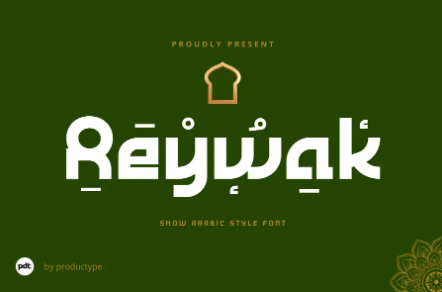
[Creativemarket] Reywak Font (2022)
Reywak - новый впечатляющий шрифт, в котором сочетаются чистый вид шрифтов sans-serif и мощная символика арабских символов. Благодаря своей удобочитаемости он идеально подходит для заголовков и длинных текстов, а уникальная привлекательность арабески прекрасно подходит для плакатов и поздравлений. Reywak: используйте его, чтобы сделать ваш контент лучше других.
Конечно, ваши различные дизайнерские проекты будут идеальными и необычными, если вы будете использовать этот шрифт, потому что этот шрифт оснащен семейством шрифтов, как для заголовков, так и для подзаголовков и текста предложений, начните использовать наши шрифты для ваших необычных проектов.
Reywak - новый впечатляющий шрифт, в котором сочетаются чистый вид шрифтов sans-serif и мощная символика арабских символов. Благодаря своей удобочитаемости он идеально подходит для заголовков и длинных текстов, а уникальная привлекательность арабески прекрасно подходит для плакатов и поздравлений. Reywak: используйте его, чтобы сделать ваш контент лучше других.
Конечно, ваши различные дизайнерские проекты будут идеальными и необычными, если вы будете использовать этот шрифт, потому что этот шрифт оснащен семейством шрифтов, как для заголовков, так и для подзаголовков и текста предложений, начните использовать наши шрифты для ваших необычных проектов.